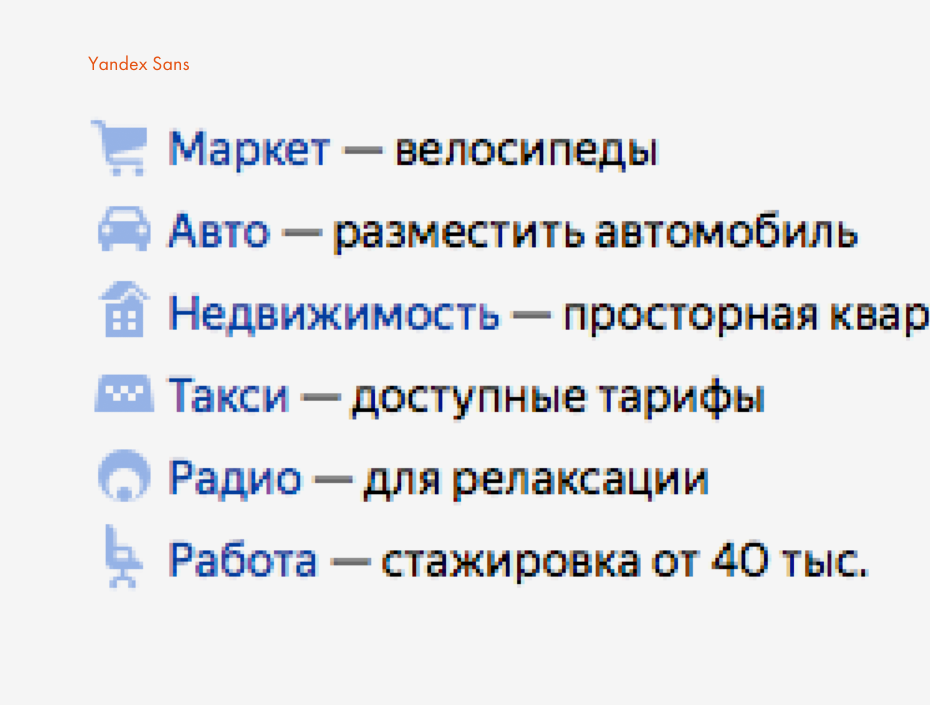
Разработка шрифта Yandex Sans
В ап­ре­ле это­го го­да ком­па­ния «Ян­декс» анон­си­ро­ва­ла соб­ствен­ный шрифт Yandex Sans. Этот шрифт раз­ра­ба­ты­вал­ся в те­че­ние двух лет Ми­ге­лем Рей­е­сом (Miguel Reyes) и Ильёй Ру­дер­ма­ном под ху­до­же­ствен­ным ру­ко­вод­ством Кри­сти­а­на Швар­ца (Christian Schwartz) в со­труд­ни­че­стве с ди­зай­не­ра­ми ком­па­нии. Мы по­го­во­ри­ли с участ­ни­ка­ми про­ек­та о це­лях, про­цес­се ра­бо­ты и осо­бен­но­стях вне­дре­ния но­во­го шриф­та в «Ян­дек­се» и его про­дук­тах.
н­декс за го­ды сво­е­го су­ще­ство­ва­ния про­явил се­бя как ком­па­ни­я с ред­ким для рос­сий­ско­го IT-сек­то­ра ка­че­ством — вни­ма­ни­ем к ви­зу­аль­но­му язы­ку и ди­зайн-мыш­ле­нию. По­сле про­дол­жи­тель­но­го со­труд­ни­че­ства со Сту­ди­ей Ле­бе­де­ва в 2009 го­ду ком­па­ния на­ча­ла­ вы­стра­и­вать соб­ствен­ный от­дел ди­зай­на. Борь­ба за луч­шие кад­ры на рын­ке, став­ка на ком­форт­ную ра­бо­чую сре­ду, ор­га­ни­за­ция об­ра­зо­ва­тель­ных ме­ро­при­я­тий — за­пуск Шко­лы ди­зай­на и про­ек­та Мо­би­ли­за­ция — всё в ко­неч­ном счёте ра­бо­та­ет на раз­ви­тие про­дук­тов и ка­пи­та­ли­за­цию ком­па­нии. До не­дав­них пор су­ще­ство­ва­ла толь­ко од­на об­ласть, ко­то­рую «Ян­декс» не спе­шил ре­фор­ми­ро­вать, — шриф­ты и ти­по­гра­фи­ка. Это по­ло­же­ние из­ме­ни­лось по ини­ци­а­ти­ве Ири­ны Во­ло­ши­ной, ди­зайн-ди­рек­то­ра «Ян­дек­са» в пе­ри­од 2013–2015 го­дов. В бли­жай­шем бу­ду­щем вне­дре­ни­е шриф­та Yandex Sans кос­нёт­ся всех про­дук­тов и мно­го­ми­лли­он­ной ауди­то­рии ком­па­нии. Остаёт­ся до­ба­вить: ис­поль­зуя свой шрифт, «Ян­декс» вы­пол­ня­ет и «са­ни­тар­ную» функ­цию, спа­са­я поль­зо­ва­те­лей от ки­рил­ли­цы шриф­та Arial.
За­чем «Ян­дек­су» свой шрифт? В ка­кой мо­мент ком­па­ния ре­ши­лась на из­ме­не­ния?
Ири­на Во­ло­ши­на: Мы за­ду­ма­лись о соб­ствен­ном шриф­те, ко­гда вста­ла за­да­ча объ­еди­не­ния всех сер­ви­сов, про­дук­тов и ком­му­ни­ка­ций в еди­ную эко­си­сте­му. «Ян­декс» раз­ви­вал­ся ак­тив­но, и за это вре­мя воз­ник­ло огром­ное ко­ли­че­ство раз­но­род­ных ре­ше­ний. Нам был не­об­хо­дим один зна­ме­на­тель для всей си­сте­мы на­ших про­дук­тов. Учи­ты­вая, что се­го­дня ин­тер­фей­сы стре­мят­ся к ми­ни­ма­лиз­му, у ди­зай­не­ра из гра­фи­че­ских вы­ра­зи­тель­ных средств остаёт­ся все­го ни­че­го: цвет, от­но­ше­ния бе­ло­го к плот­но­му пят­ну, об­щая пла­сти­ка, а всё осталь­ное — это ти­по­гра­фи­че­ские ре­ше­ния. По­это­му ба­зо­вый кир­пи­чик — это, ко­неч­но, шрифт.
Мы ре­ши­ли, что нам нуж­но уни­вер­саль­ное шриф­то­вое се­мей­ство, ко­то­рое ра­бо­та­ло бы в ком­му­ни­ка­ци­ях и в про­дук­тах. Эти тре­бо­ва­ния по боль­шо­му счёту про­ти­во­ре­чат друг дру­гу: ком­му­ни­ка­ци­ям ну­жен ха­рак­тер и за­по­ми­на­е­мость, а сер­ви­сам — удоб­ство, чи­та­бель­ность и бóль­шая, чем в ком­му­ни­ка­ци­ях, ви­зу­аль­ная ней­траль­ность. Бы­ло до­воль­но не­про­сто сов­ме­стить столь раз­ные осо­бен­но­сти и со­здать один шрифт, со­от­вет­ству­ю­щий этим тре­бо­ва­ни­ям. Нам важ­но бы­ло оста­вать­ся за­по­ми­на­е­мы­ми на чу­жих тер­ри­то­ри­ях, на чу­жих плат­фор­мах и опе­ра­ци­он­ных си­сте­мах, а про­дук­там со­хра­нять свою кросс-про­дук­то­вую цель­ность, при этом не раз­дра­жая поль­зо­ва­те­лей. И мы шли к та­кой бес­шов­ной струк­ту­ре, где лю­бые эле­мен­ты си­сте­мы про­дук­тов ра­бо­та­ли бы ор­га­нич­но, ис­поль­зуя еди­ный гра­фи­че­ский язык.
Вне­дре­ние но­во­го шриф­та в су­ще­ству­ю­щую ди­зайн-сре­ду не­ми­ну­е­мо свя­за­но с опре­делён­ным стрес­сом для поль­зо­ва­те­лей. По­рой счи­та­ет­ся, что ­если поль­зо­ва­тель ни­че­го не за­ме­тил (не ис­пы­тал не­га­тив­ных эмо­ций) — это уже хо­ро­шо, и мно­гие скеп­ти­ки, учи­ты­вая этот ар­гу­мент, счи­та­ют не­це­ле­со­об­раз­ной по­доб­ную ра­бо­ту. Как вы опре­де­ля­е­те для се­бя цен­ность ре­зуль­та­та и как вос­при­ня­ли ва­ши из­ме­не­ния поль­зо­ва­те­ли?
Кон­стан­тин Гор­ский: Глав­ная цен­ность со­сто­ит в том, что у на­ше­го ви­зу­аль­но­го язы­ка по­яв­ля­ет­ся свой го­лос, ко­то­рый смо­жет зву­чать во всех сре­дах, на всех устрой­ствах. Это по­мо­жет про­дук­там и ком­му­ни­ка­ци­ям «Ян­дек­са» стать цель­нее и вы­ра­зи­тель­нее. Поль­зо­ва­те­ли мо­гут не за­ме­чать, что где-то из­ме­нил­ся шрифт, но да­же ко­гда лю­ди не впол­не спо­соб­ны вер­ба­ли­зи­ро­вать ощу­ще­ния, они всё рав­но чув­ству­ют: что-то ста­ло чуть по-дру­го­му. Если взять и по­ло­жить ря­дом скрин­шо­ты се­го­дняш­не­го «Ян­дек­са» и ка­ко­го-то ва­ри­ан­та из про­шло­го, ска­жем, двух- или трёхлет­ней дав­но­сти, раз­ни­ца ста­нет оче­вид­на каж­до­му.
Ко­гда мы го­во­рим об об­ра­зах и ин­то­на­ци­ях в шриф­те, по­яв­ля­ет­ся боль­шой риск ока­зать­ся в по­ле бес­ко­неч­ных субъ­ек­тив­ных ин­тер­пре­та­ций. Рас­ска­жи­те, как вы ис­ка­ли нуж­ные ин­то­на­ции, до­го­ва­ри­ва­лись с ди­зай­не­ра­ми, опре­де­ля­ли об­раз? Как при­ни­ма­лись ре­ше­ния вну­три ко­ман­ды?
Кон­стан­тин Гор­ский: Ока­за­лось, что на­ши со­труд­ни­ки до­воль­но по­хо­жим об­ра­зом пред­став­ля­ют се­бе «Ян­декс». Ви­ди­мо, цен­но­сти ком­па­нии иг­ра­ют в этом не по­след­нюю роль, и это здо­ро­во. Мы по­пы­та­лись рас­ска­зать об этом Кри­сти­а­ну Швар­цу и Илье Ру­дер­ма­ну, по­ка­зы­ва­ли им на­ши про­дук­ты, эво­лю­цию на­ше­го ди­зай­на и но­вые на­ра­бот­ки. А они пред­ла­га­ли скет­чи, ва­ри­ан­ты ха­рак­те­ра шриф­та, из ко­то­рых мы вы­би­ра­ли. При­ня­тие ре­ше­ний бы­ло, ска­жем так, очень не­про­стым, по­сколь­ку мы при­вык­ли вни­ма­тель­но от­но­сить­ся к мне­нию каж­до­го, а мне­ний бы­ло очень и очень мно­го. От­ча­сти это ста­ло при­чи­ной то­го, что про­цесс вы­шел дол­гим и не­про­стым. Ран­ние вер­сии шриф­та ди­зай­не­ры те­сти­ро­ва­ли в про­дук­тах, од­на­ко про­во­дить серьёз­ные экс­пе­ри­мен­ты с жи­вой ауди­то­ри­ей с не­хин­то­ван­ной или не­от­кер­нен­ной вер­си­ей шриф­та не­воз­мож­но, по­это­му мно­гие те­сти­ро­ва­ния ещё толь­ко пред­сто­ят. Тут как с ди­зай­ном про­дук­тов: на­сто­я­щий ди­зайн на­чи­на­ет­ся толь­ко по­сле за­пус­ка.
Од­ним из тре­бо­ва­ний к раз­ра­бот­чи­кам Yandex Sans бы­ло сле­до­ва­ние клю­че­вым па­ра­мет­рам — мет­ри­кам и про­пор­ци­ям — си­стем­но­го шриф­та Arial. Это мож­но по­нять с праг­ма­тич­еской точ­ки зре­ния: шрифт встаёт на своё ме­сто в ин­тер­фей­се, не раз­би­вая ма­ке­ты, но при этом даёт опре­делён­ные огра­ни­че­ния в ди­зайн-ре­ше­ни­ях. Как это ока­за­лось на прак­ти­ке? Ка­кую пер­вую обрат­ную связь вы по­лу­чи­ли?
Кон­стан­тин Гор­ский: Мы вы­ка­ты­ва­ли шрифт в те­сти­ро­ва­ние во вну­трен­нем бло­ге «Ян­дек­са», но этот экс­пе­ри­мент не сто­ит вос­при­ни­мать всерьёз. Я да­же не уве­рен, что сло­во «экс­пе­ри­мент» здесь при­ме­ни­мо. Те со­труд­ни­ки, ко­то­рые столк­ну­лись с но­вым шриф­том, ни­че­го не за­ме­ти­ли. И это здо­ро­во, это го­во­рит о том, что чте­нию и вос­при­я­тию ин­фор­ма­ции ни­че­го не по­ме­ша­ло. Од­ним из са­мых по­лез­ных след­ствий это­го те­сти­ро­ва­ния ста­ло то, что лю­ди уви­де­ли шрифт не толь­ко на экра­нах ди­зай­нер­ских мо­ни­то­ров, но и на са­мых раз­ных устрой­ствах, в раз­ных бра­у­зе­рах, на­при­мер, с вы­клю­чен­ным экран­ным сгла­жи­ва­ни­ем. Всё это да­ло цен­ную обрат­ную связь, ко­неч­но.